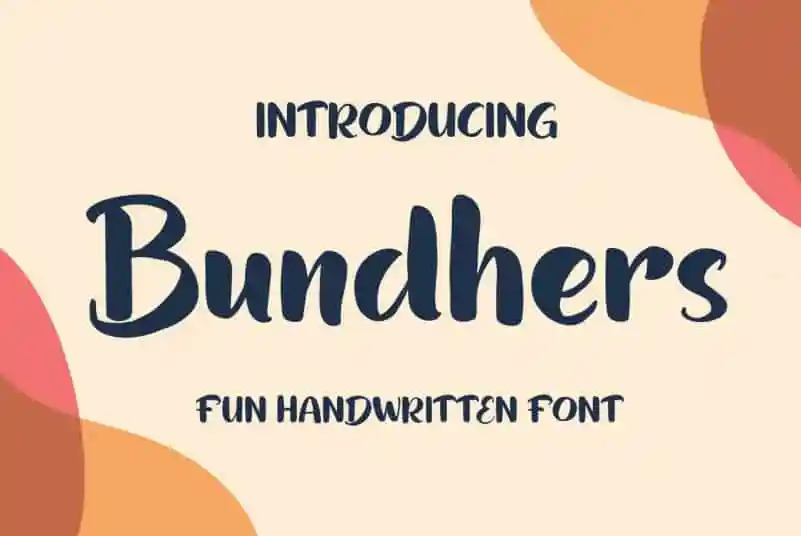
A ‘Bundhers Brush Font’ é uma tipografia à mão escrita que oferece uma versão realista do estilo de escrever a mão, projetada para várias aplicações e mídias. Esta fonte é perfeita para criar um visual moderno e sofisticado em designs como capas de livros e revistas, conteúdos sociais, rótulos, logotipos, artesanato, produtos confeccionáveis e até mesmo produtos digitais. Uma das suas principais vantagens é sua versatilidade: ela pode ser usada tanto em letras maiúsculas quanto minúsculas e inclui um conjunto de números e símbolos, o que a torna ainda mais completa e útil para os designers que buscam personalizar diferentes projetos. O fato de estar disponível em várias línguas também adiciona uma dimensão extra ao seu uso, permitindo que você utilize esta fonte de maneira multilíngue. Com sua natureza à mão e o design cuidadosamente elaborado, a ‘Bundhers Brush Font’ é perfeita para quem busca um toque elegante em seus trabalhos. Combinada com suas múltiplas opções de uso, ela oferece uma fonte completa que vai transformar qualquer projeto em algo único e imediatamente reconhecível. Aprecie a qualidade desta fonte e explore as inúmeras possibilidades criativas à sua disposição.